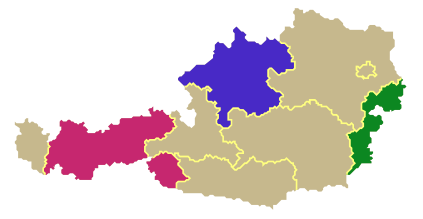
frage: kann es sein, dass die linien der grenzen (nicht der länderflächen) leicht unsauber sind, bzw. ausreißer haben?
Ja, da muss ich noch mal heftig dran feilen, ich hatte die in Fontlab gebaut, aber das macht da heftig schrott - und das, obwohl die Linien eigentlich hätten genau aufs Raster treffen müssen.
Diese Ungenauigkeiten bei den Fontlab-Actions (hier besonders die Effekte) sind echt zum Kotzen.
Ich hab diese Grenzen-Grafik jetzt lieber in Corel gemacht, da musste ich zwar auch noch mächtig Knoten von Hand löschen, weil auch da die Konturen-Vereinfachungs-Funktion auch die falschen Knoten löscht, nämlich die an den Ecken statt derer, die mitten auf einer Geraden sitzen, aber auf alle Fälle ist das Ergebnis viel besser, als der Schrott, den mit Fontlab liefert.
Derzeit erweitere ich das auch noch, wie die Tyskland45 um die Besatzungszonen.
Der Kelch mit einer ÖDR oder VRÖ aus halb Oberösterreich, Niederöstereich und dem Burgenland, mit Ostwien als Haupstadt ist ja an Euch Ösis vorbei gegangen.
So, hier jetzt alle Codes:
Ganz Österreich als Hintergrund: #Ab oder #Österreich
Bundesländer:
Vorarlberg: #VA oder #Vorarlberg
Tirol: #TI oder #Tirol
Salzburg: #SA oder #Salzburg
Oberösterreich: #OO oder #Oberösterreich
Niederösterreich: #NO oder #Niederösterreich
Burgenland: #BL oder #Burgenland
Steiermark: #SM oder #Steiermark
Kärnten: #KA oder #Kärtnten
Wien: #WI oder #Wien
Besatzungszonen 1945 - 55:
Französische Zone: #ZF oder #Franz
Amerikanische Zone: #ZA oder #Amerika
Sovietzone: #ZS oder #Soviet
Britische Zone: #ZB oder #Brit
Wien Französische Zone: #WF oder #WienF
Wien Amerikanische Zone: #WA oder #WienA
Wien Sovietzone: #WS oder #WienS
Wien Britische Zone: #WB oder #WienB
Grenzlinien mit Außengrenze: #Ag oder #Grenzen
nur Binnengrenzen (für abschließende Rahmen): #Ac oder #Innen
Alle Glyhen zuvor hatten Nullbreite, stapeln sich also übereinander ohne Vorschub, Es folgt jetzt der Abschluss mit einem Zeichen, das die komplette Kartenbreite hat:
Rahmen (Außengrenze)
dünne Kontur: #At oder #Dünner
dickere Kontur: #Af oder #Dicker
Kontur mit Schatten: #As oder #Schatten
Karte auf Quadrat: #Aq oder #Quadrat
Karte aud Ellipse: #Ao oder #Oval
Abschluss ohne Rahmen (extrabreites Leerzeichen): #Al oder #Leer
Die Codes am besten mit irgend einer anderen Schrift eingeben, Schriftfarben zuweisen und erst dann auf Austria45 schalten, aber das hatten wir bei Tyskland45 schon.
Hier ein Muster: 3 Länder auf generellem Hintergrund und Binnengrenzen:
und der farbige Code dazu: